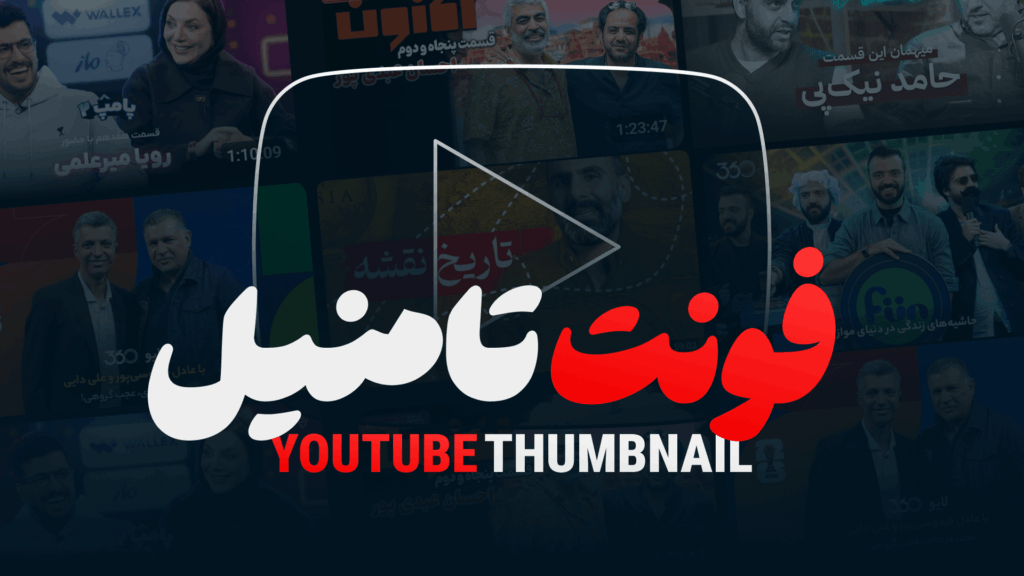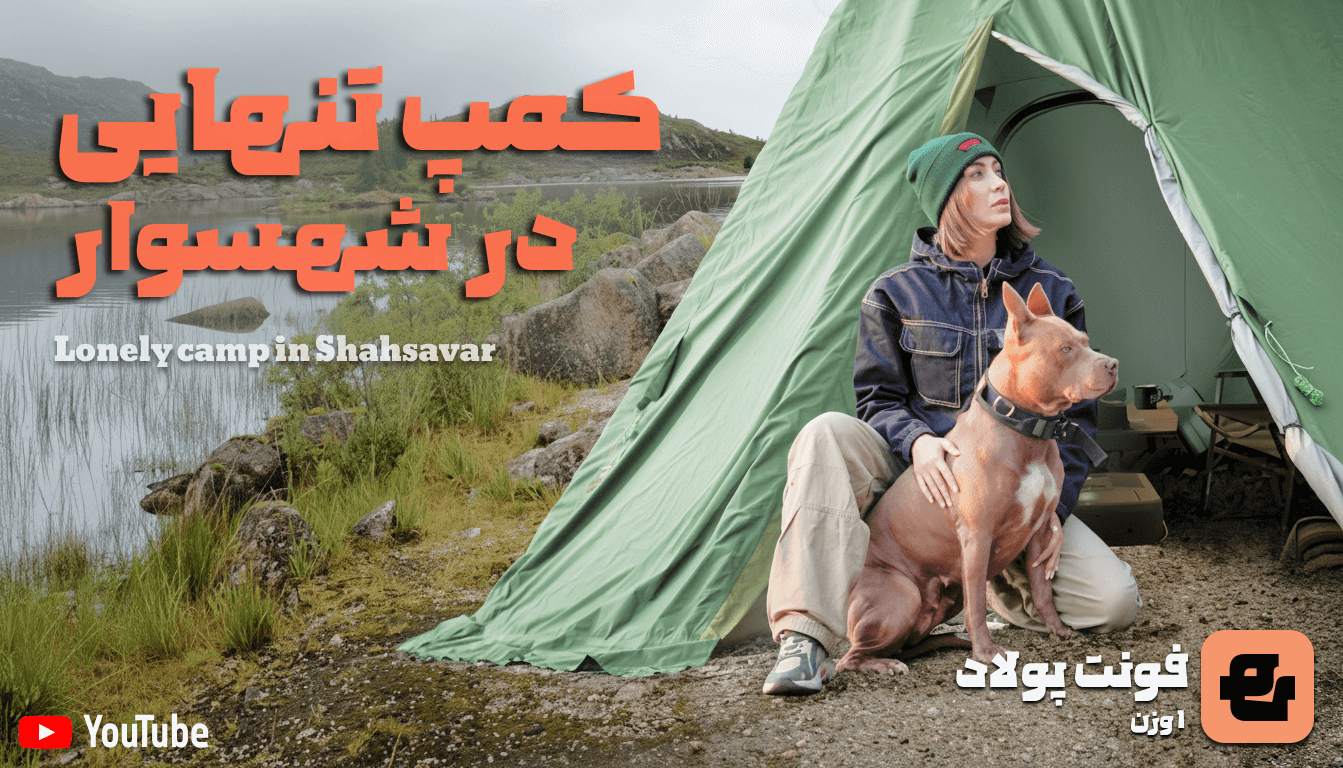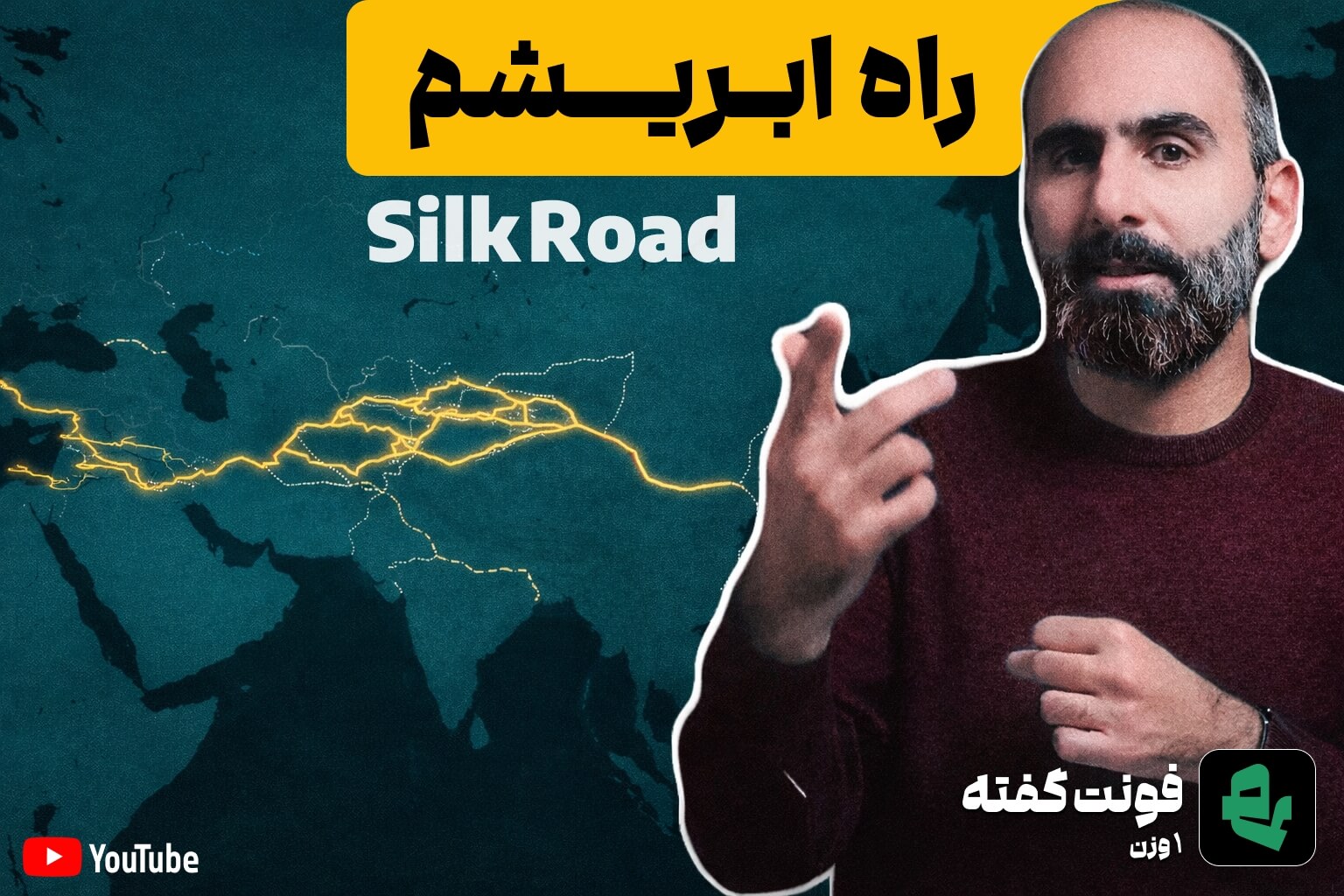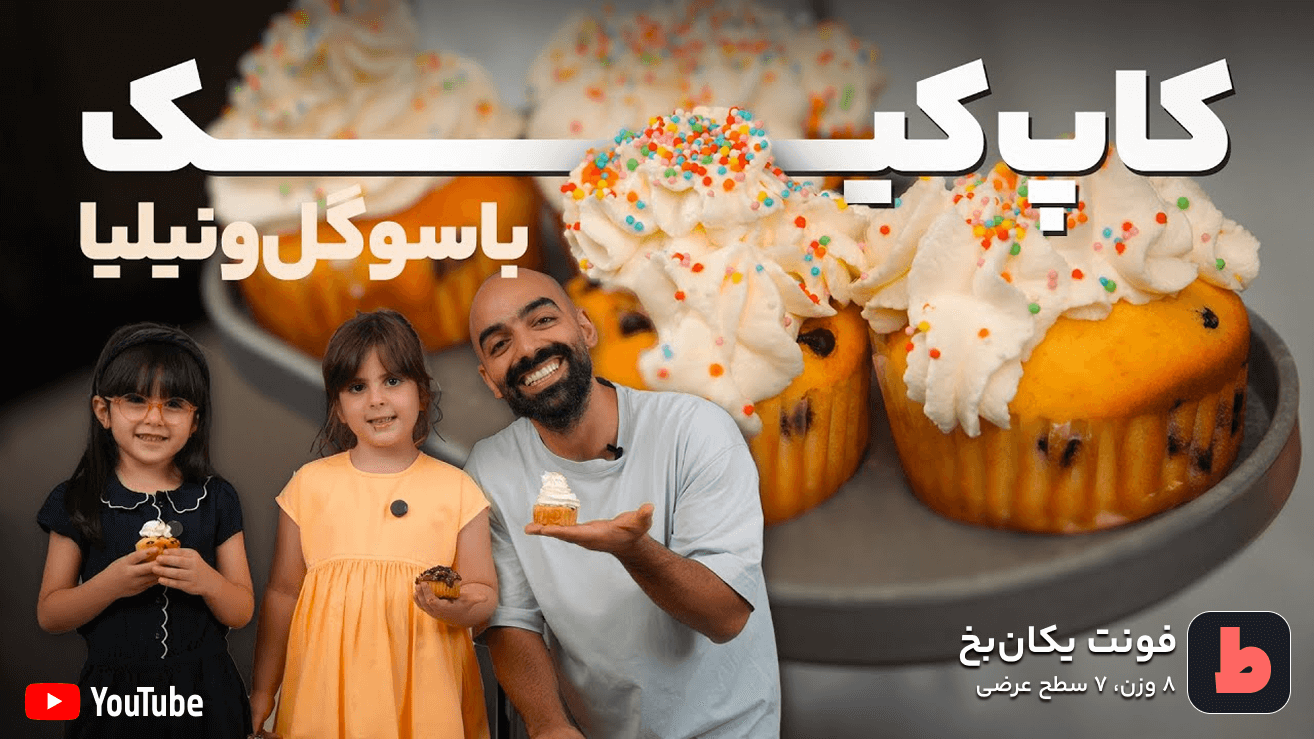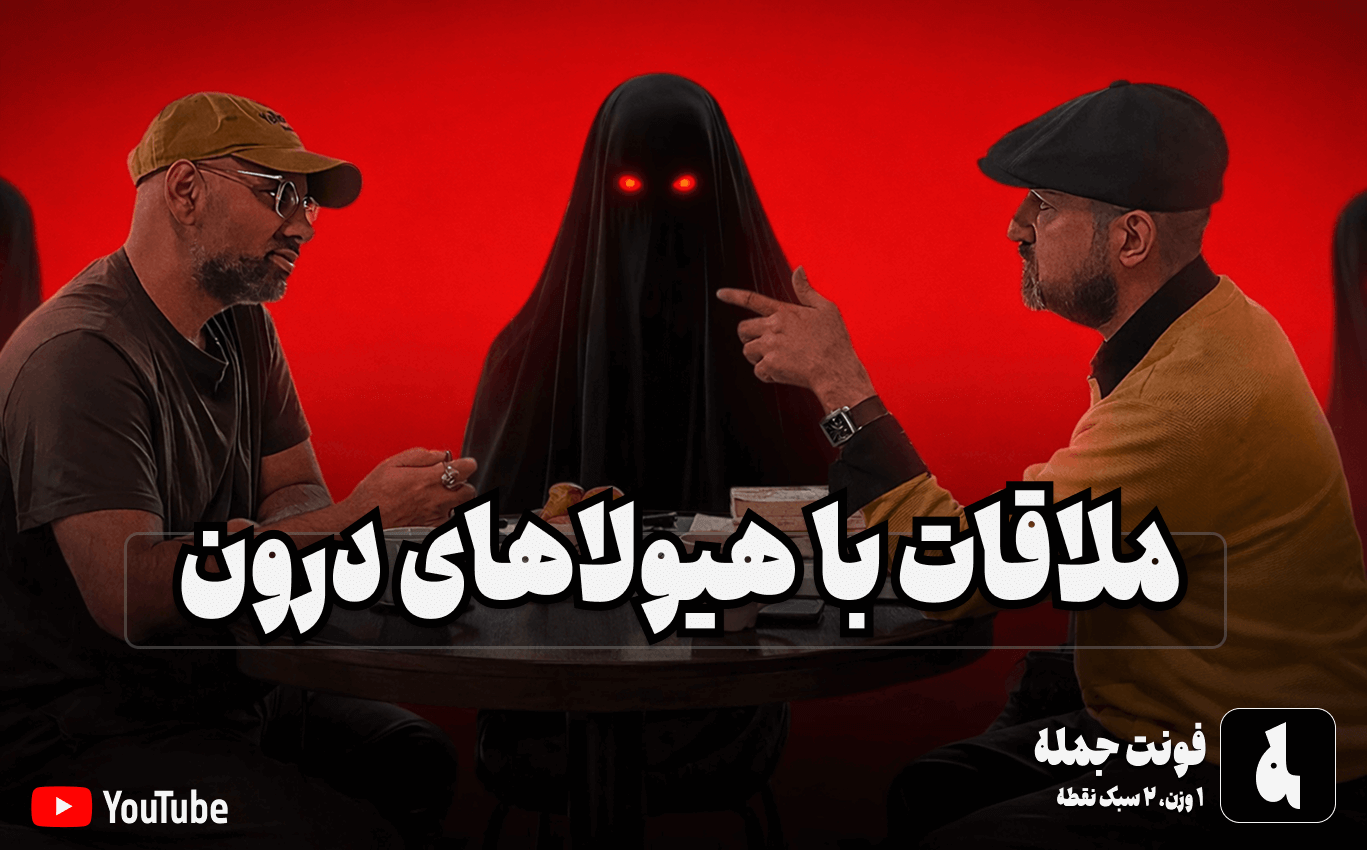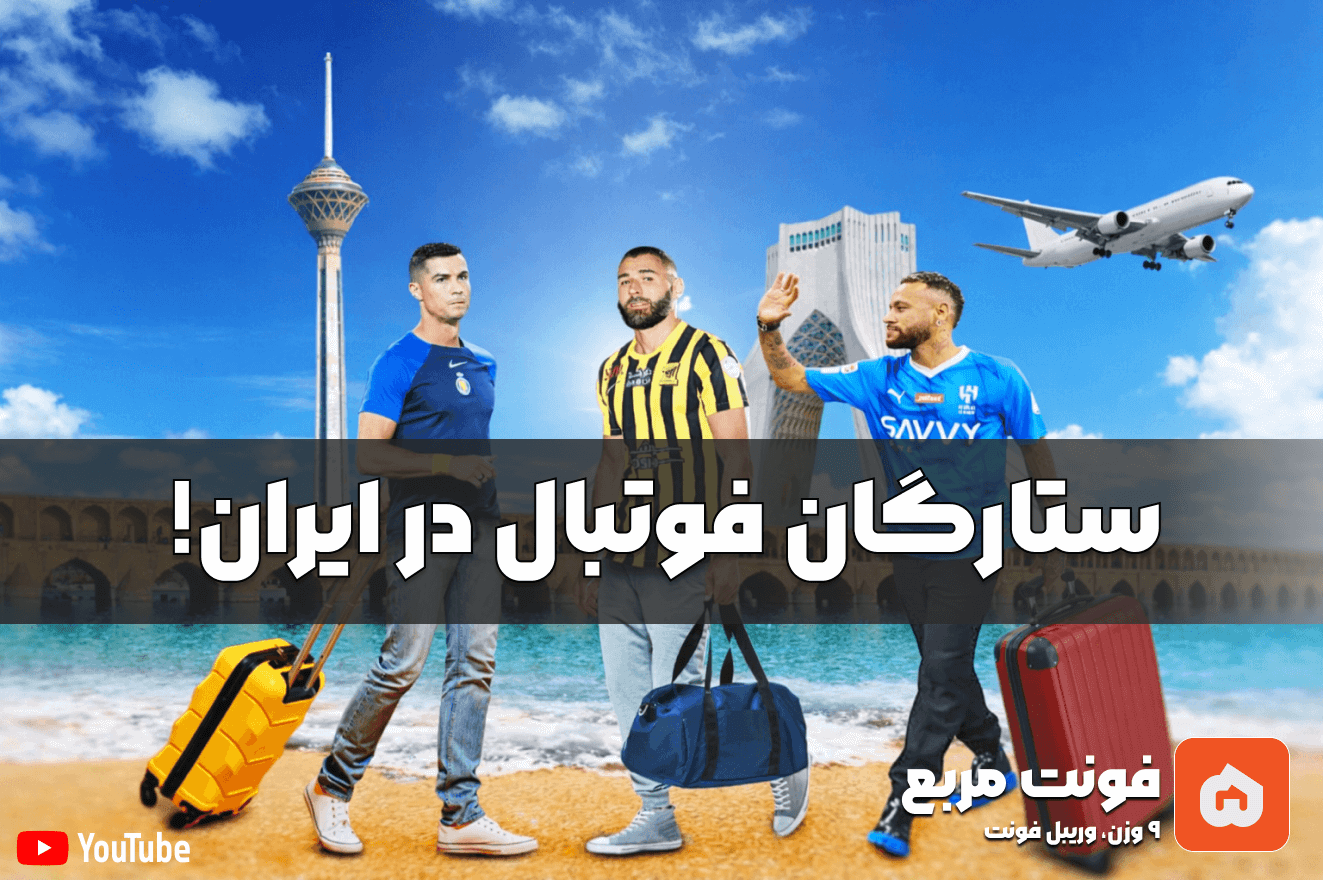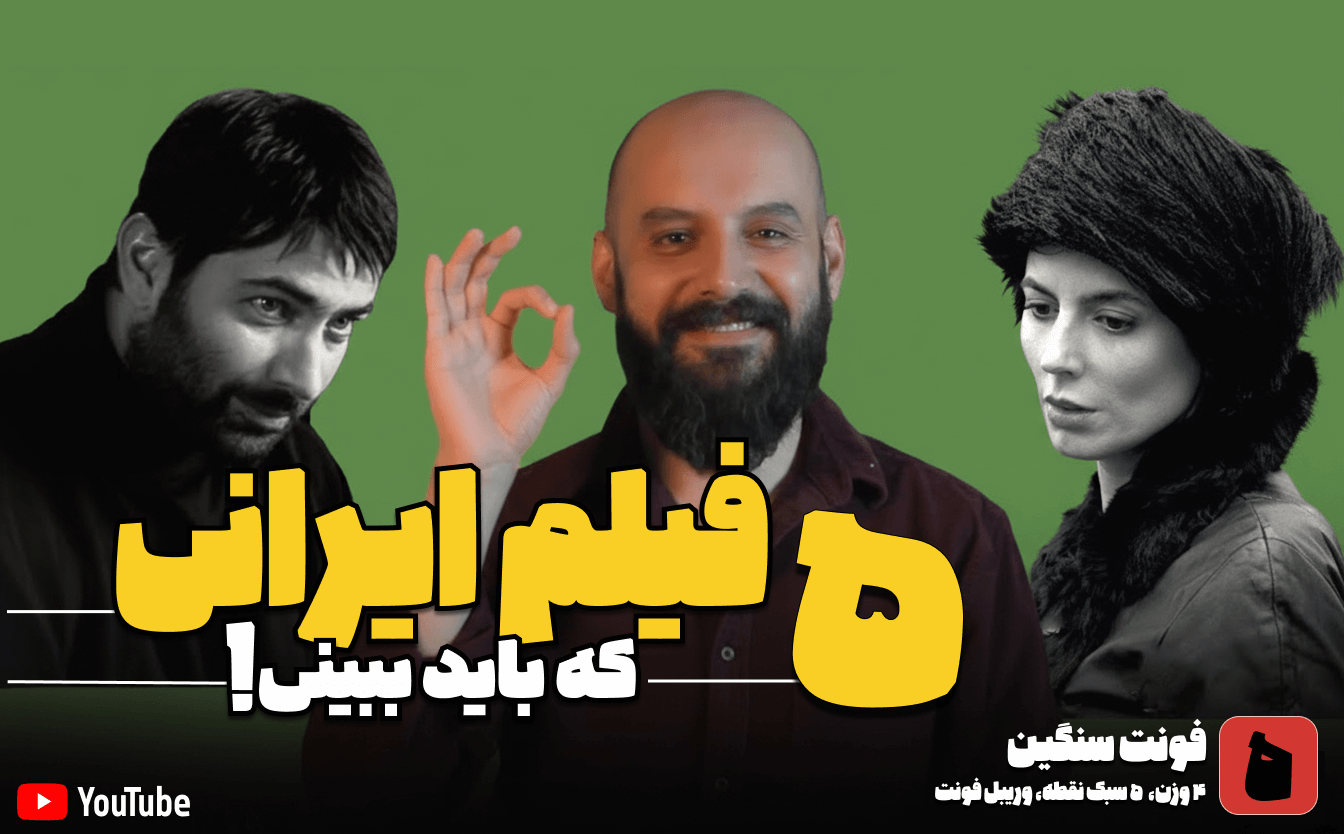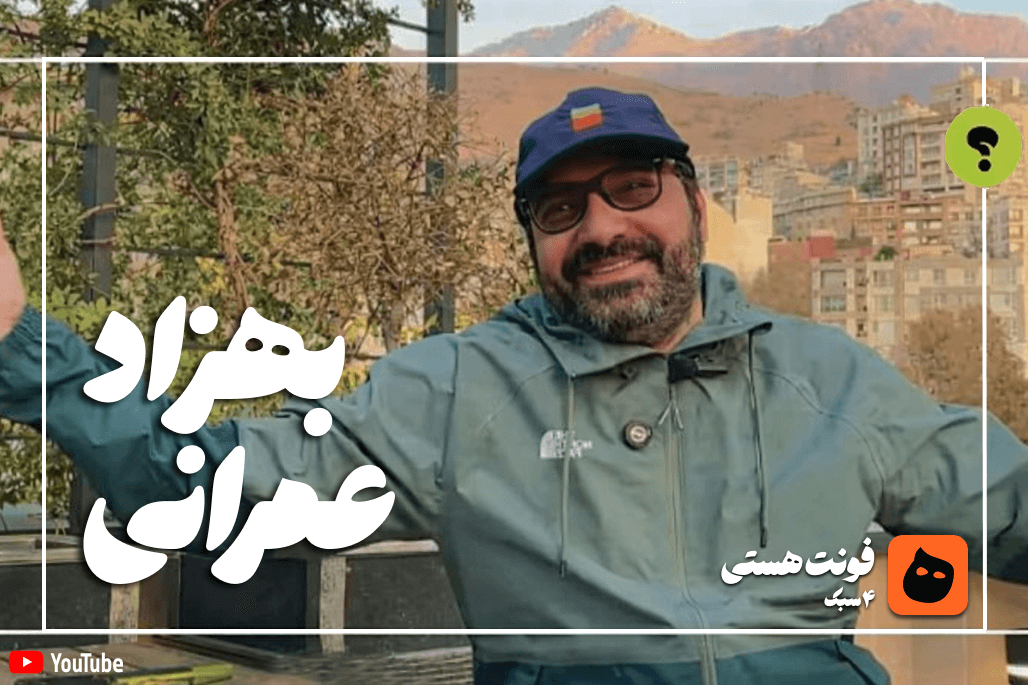
فونت‌های مناسب تامنیل یوتیوب (YouTube Thumbnail)
تامنیل ویدیوی شما در یوتیوب، بیلبورد محتوای شماست. با افزایش رقابت در شبکه‌های اجتماعی، مخاطب در چند ثانیه تصمیم می‌گیرد که روی ویدیوی شما کلیک کند یا از آن رد شود. حتی ارزشمندترین ویدیوها، بدون تامنیل(کاور) حرفه‌ای، شانس دیده‌شدن را از دست می‌دهند.
از آنجا که متن تامنیل معمولاً کوتاه و حدود 2 تا ۵ کلمه است، هر کلمه باید حداکثر تأثیر را داشته باشد. فونت مناسب باید باعث شود تیتر در همان نگاه اول، دیده و خوانده شود.
ویژگی‌های فونت مناسب برای تامنیل یوتیوب
1. ساده و بدون حروف تزئینی
در تامنیل، جایی که زمان تصمیم‌گیری بیننده تنها چند ثانیه است، سادگی نقش مهمی در انتقال سریع پیام دارد. فونت‌های مخصوص تامنیل با حذف تزئینات و انحناهای اضافی، ظاهری ساده، منظم و قابل‌فهم ایجاد می‌کنند و باعث افزایش خوانایی می‌شوند. برای این سبک، استفاده از فونت‌های ایران یکان و یکان بخ پیشنهاد می‌شود.
2.کنتراست بالا؛ راز دیده‌شدن سریع متن
فونت‌های با کنتراست بالا، فراتر از زیبایی‌شناسی، ابزاری حرفه‌ای برای افزایش خوانایی، جلب توجه و حفظ وضوح متن در شرایط بصری محدود هستند. این فونت‌ها در طراحی تامنیل، تبلیغات موبایلی و هر جایی که زمان و فضای دید مخاطب محدود است، نقش کلیدی ایفا می‌کنند.
برای کاربران موبایل ایجاد تضاد رنگی مناسب بین متن و پس‌زمینه اهمیت دارد. افزودن Outline سفید یا سیاه یا Drop Shadow باعث می‌شود متن از پس‌زمینه جدا شود و بیشتر در چشم بیننده دیده شود.
۳. ساختار قوی با فضاهای منفی کم
فضای منفی کمتر به معنای حروف جمع‌وجورتر و ضخیم‌تر است که حتی در صفحه‌های کوچک مانند موبایل نیز خوانایی خود را حفظ می‌کنند. این ویژگی باعث می‌شود متن در ابعاد کوچک کم‌رنگ، محو یا ناخوانا نشود. برای استفاده از این ویژگی، فونت های کولاک، سنگین و هستی  پیشنهاد می شود.
4.استفاده از فونت بولد
تامنیل فضای محدودی دارد، بنابراین استفاده از فونت‌های ضخیم باعث افزایش قدرت بصری و جلب توجه سریع مخاطب می‌شود. فونت بولد کمک می‌کند متن در میان پس‌زمینه‌های شلوغ به‌راحتی دیده شود. برای این سبک، استفاده از فونت‌های «گفته»، «جمله» و «پولاد» پیشنهاد می‌شود.
۵. تست در اندازه کوچک
قبل از انتشار، تامنیل را با زوم ۲۰ درصد مشاهده کنید. اگر نوشته هنوز واضح و قابل‌تشخیص باشد، فونت مناسب است. در غیر این صورت، ضخامت یا نوع فونت را تغییر دهید.
قبل از انتشار هر ویدیو یوتیوب از خود بپرسید:  اگر این تامنیل را در فید شلوغ یوتیوب ببینم، آیا روی آن کلیک می‌کنم؟ اگر پاسخ شما مثبت است، یعنی انتخاب فونت و طراحی شما دقیق و مؤثر بوده است.